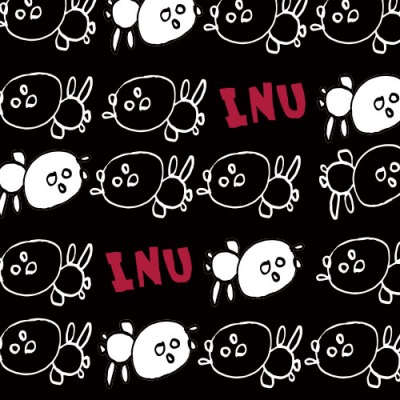
イヌ
Artist重田陽子
Designer岩間 美空
Organizationむつみ工房
渋谷の顔とも言えるハチ公像をキッチュにデザイン。暗めの彩色にすることで渋谷がキッチュなだけではなくクールな面も持つ最先端の街であることを表現した。(岩間 美空)
犬かな?熊かな?ご本人に言わせると…(むつみ工房)